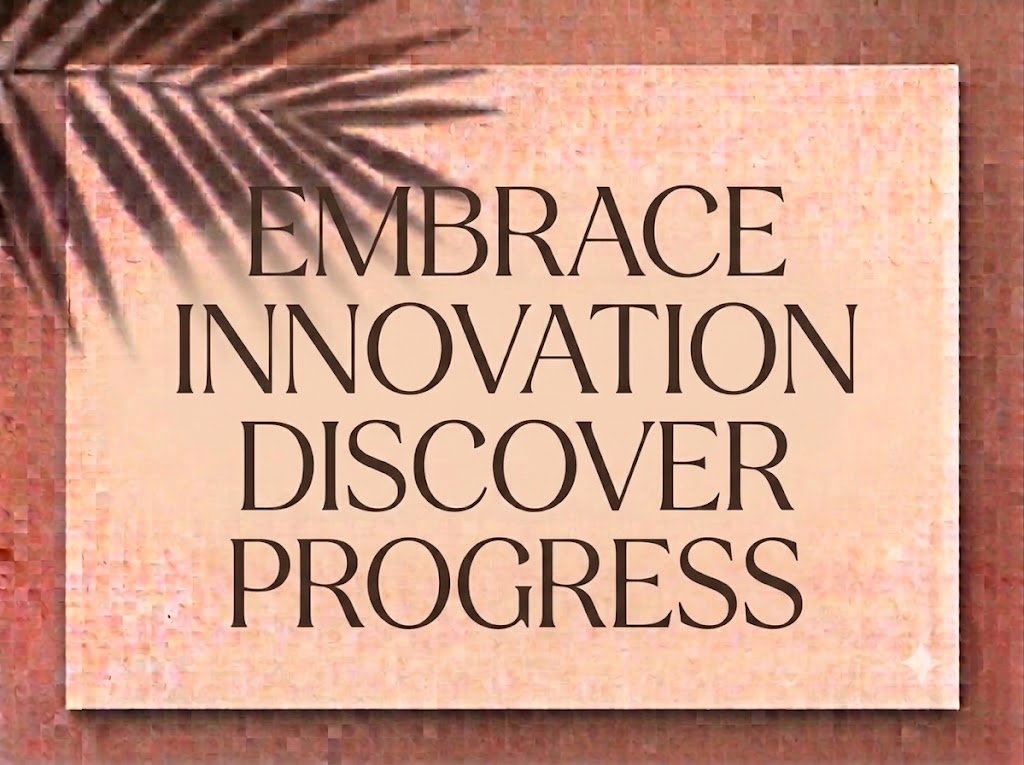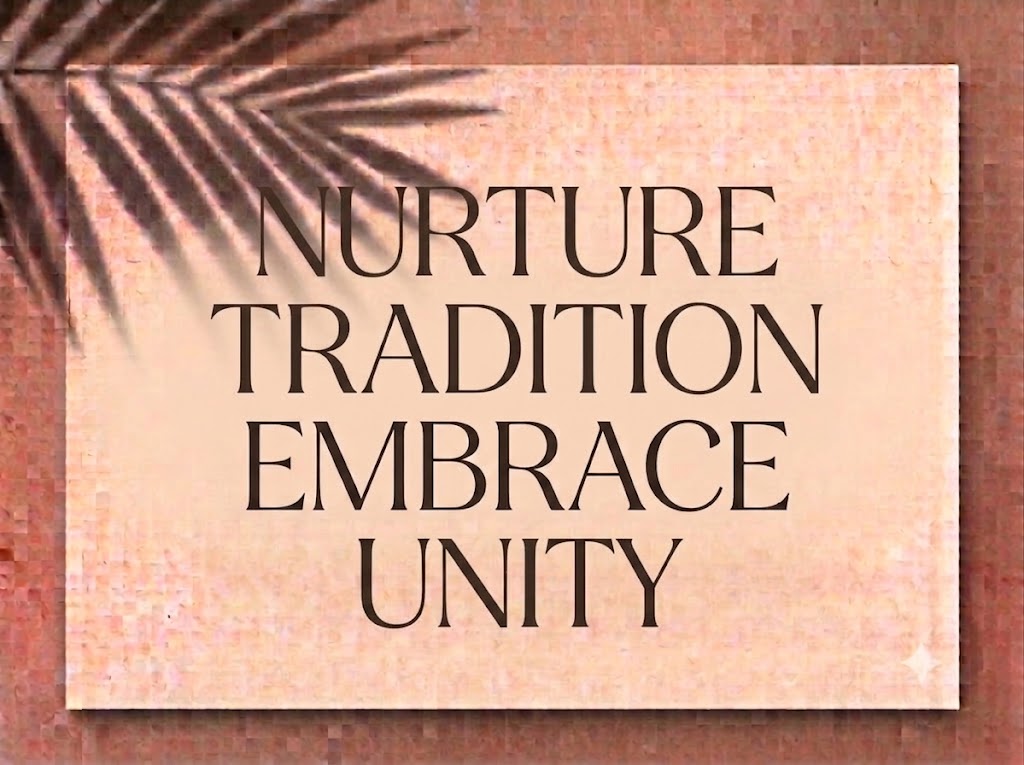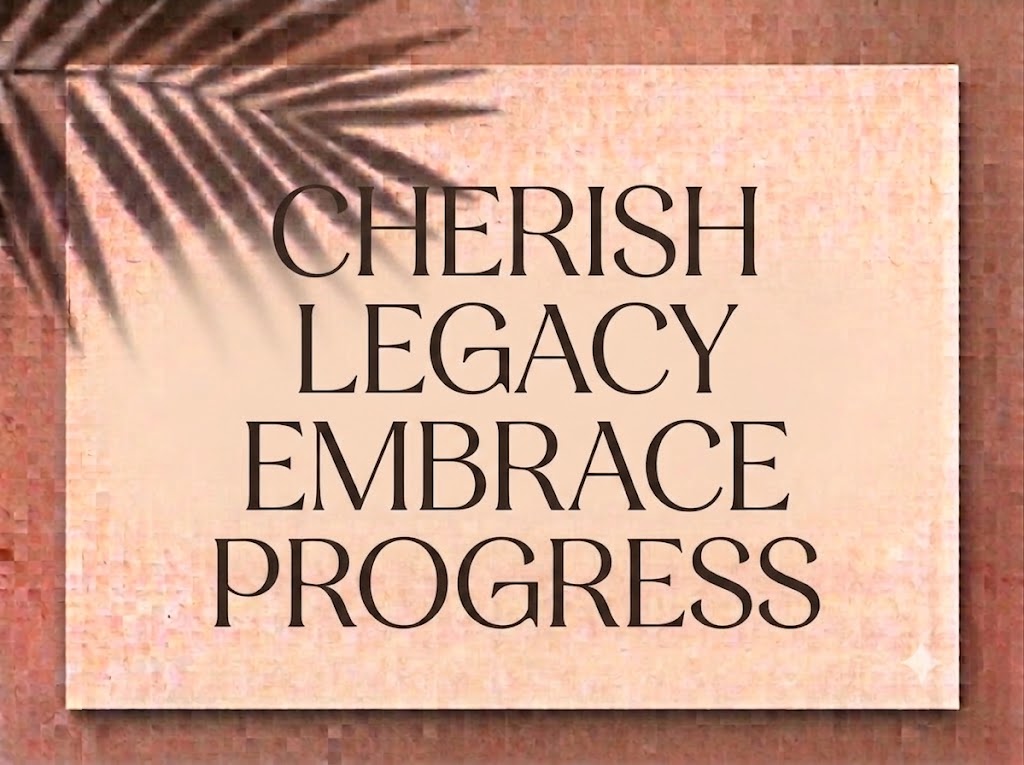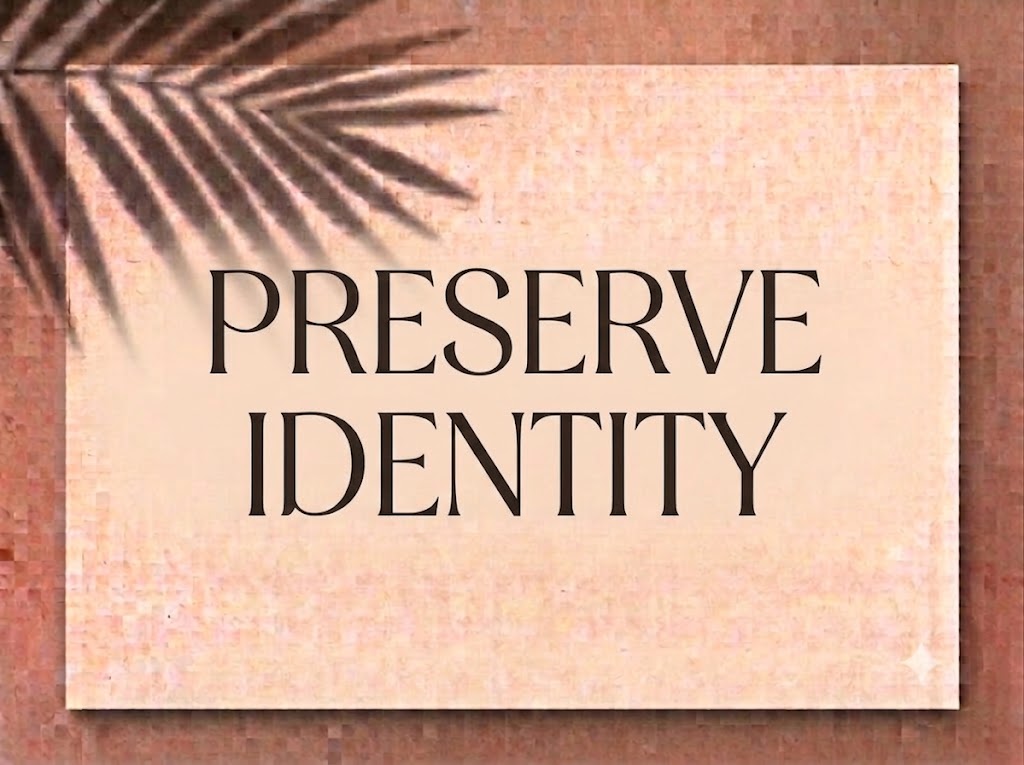
1FTV Maglony
Trong thiết kế đồ họa thời trang, mỹ phẩm và các ấn phẩm phong cách sống, những kiểu chữ Serif sở hữu nét uốn lượn bay bổng luôn giữ vị thế vô cùng đặc biệt. Một dòng tiêu đề được tạo hình tinh tế không chỉ truyền tải thông điệp ngắn gọn mà còn mang lại cảm xúc sang trọng, mềm mại và đầy tính nghệ thuật.
Nếu bạn đang tìm kiếm một phông chữ hiển thị mang hơi hướng tân cổ điển với các đường cong quyến rũ cho bìa tạp chí, lookbook hay tiêu đề video ngắn, font 1FTV Maglony chính là sự lựa chọn rất đáng cân nhắc.
Giới thiệu về font 1FTV Maglony
Font 1FTV Maglony là bộ chữ hiển thị có chân (serif display) mang phong cách tân cổ điển hiện đại, nổi bật với sự giao thoa giữa nét chữ có chân kiêu sa và các đường nét uốn lượn nghệ thuật:
Tên phông chữ: 1FTV Maglony
Đặc điểm nổi bật của phong cách thiết kế Maglony
Sức hút thị giác của font 1FTV Maglony đến từ sự uốn lượn mềm mại và nét tương phản kịch tính giữa các thanh nét:
Nét uốn lượn cách điệu duyên dáng: Đuôi chữ uốn cong mềm mại ở các ký tự như f, g, y, j, r. Chữ f có phần đuôi vươn nhẹ nhàng, chữ g sở hữu nét móc dưới mở rộng bay bổng, mang lại cảm giác nữ tính và thanh thoát.
Độ tương phản thanh đậm kịch tính: Sự chênh lệch rõ rệt giữa các cột dọc vững chãi và nét ngang mỏng nhẹ mang lại chiều sâu nghệ thuật, gợi liên tưởng đến trang bìa của các tạp chí thời trang cao cấp.
Hỗ trợ chữ hoa và chữ thường đồng bộ: Phông chữ tích hợp đầy đủ hệ thống chữ cái viết hoa và viết thường, giúp các nhà thiết kế dễ dàng kết hợp để tạo ra nhịp điệu chữ thoáng đãng và tự nhiên.
Khoảng cách giữa các chữ (kerning) và độ giãn dòng được tính toán chuẩn xác, giúp các đường uốn lượn của ký tự khi đứng cạnh nhau không bị dính nét hay rối mắt.
Tích hợp trọn vẹn bộ chữ cái hoa – thường, dãy chữ số 0-9 dáng đứng thanh lịch cùng hệ thống ký tự đặc biệt, dấu câu thông dụng.
Hình ảnh demo thực tế của font 1FTV Maglony
Khả năng hiển thị của phông chữ này được tối ưu rất tốt trên nhiều tỷ lệ kích thước khác nhau:
Kích thước nhỏ (12pt – 24pt): Nhờ cấu trúc chữ đứng ngay ngắn và khoảng hở nội tại rõ ràng, bộ chữ thường và dãy số vẫn hiển thị sắc nét, ngay hàng thẳng lối trên màn hình di động.
Kích thước lớn (36pt – 72pt): Đây là đất diễn lý tưởng nhất để 1FTV Maglony phô diễn toàn bộ sự kiêu sa, quyến rũ của các đường nét uốn lượn ở chữ f, g, y, tạo tác động thị giác mạnh mẽ cho các dòng tiêu đề chính.
Ứng dụng trong thiết kế đồ họa và làm video
Sở hữu nét cá tính thanh lịch và đầy tính nghệ thuật, font 1FTV Maglony mở ra không gian ứng dụng phong phú:
Video ngắn (TikTok, Reels, Shorts): Phông chữ serif dáng uốn lượn này hiển thị rất đẹp trên khung hình đứng tỷ lệ 9:16. Nó cực kỳ ăn nhập với các video vlog phong cách sống, review mỹ phẩm, trang sức hay thời trang nghệ thuật.
Ảnh thu nhỏ YouTube (Thumbnail): Vũ khí tuyệt vời cho các kênh làm nội dung về âm nhạc lofi, acoustic, chữa lành hoặc review đồ hiệu nhờ giao diện chuyên nghiệp và thu hút.
Thiết kế bìa tạp chí, Lookbook và Poster: Hoàn hảo cho các sản phẩm truyền thông thuộc lĩnh vực thời trang, spa, váy cưới, mỹ phẩm hoặc triển lãm nghệ thuật.
Nhận diện thương hiệu phân khúc Luxury: Thích hợp làm logo dạng chữ khối, menu nhà hàng hay khách sạn sang trọng, thiệp mời sự kiện VIP và bao bì nước hoa cao cấp.